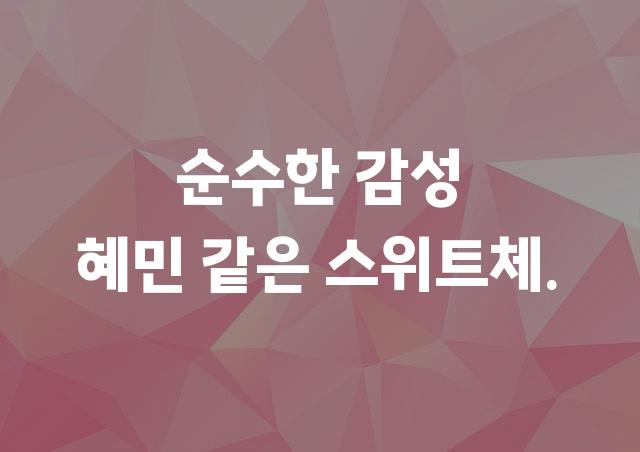
‘수트’는 문서 작성에 최적화된 기본 고딕 폰트로, 선명하고 깨끗한 라인이 특징입니다. 다양한 문서에서의 가독성을 높이고, 감성적인 느낌을 전달합니다.
수트은(는)
기본 고딕, 감성적인, 부드러움 계열의 생김새를 가지고 있으며
로고 디자인, 브랜딩 등에서 자주 활용되며, 효과적인 메시지 전달에 적합합니다.
이 폰트는 패션/뷰티, 금융/비즈니스 분야에 잘 어울리며,
세련된, 고급스러운 느낌을 담고 있는 것이 특징입니다.